In de Adobe CC apps kon je al een tijdje met variable fonts werken. Sinds de laatste update van Figma is het daar nu ook mogelijk. Maar waar zit die optie nou precies? En wat zijn de beste use cases? Figma komt met antwoorden en tips:
De presentatie bestaat uit vier delen: een introductie over wat variable fonts zijn, een demo van hoe je ze in Figma gebruikt, wat achtergronden bij de totstandkoming van de feature, en antwoorden op de meest gestelde vragen. Ik vond de hele video zeer de moeite waard :)
Voor wie met variable fonts wil spelen maar ze nog niet heeft geïnstalleerd, heb ik mijn favoriete variable Google Fonts op een rij gezet. Natuurlijk zijn er veel betere en bijzonderdere variable fonts out there, maar als je snel en gratis aan de slag wil, check dan deze:
Variable Google Fonts die niet zuigen
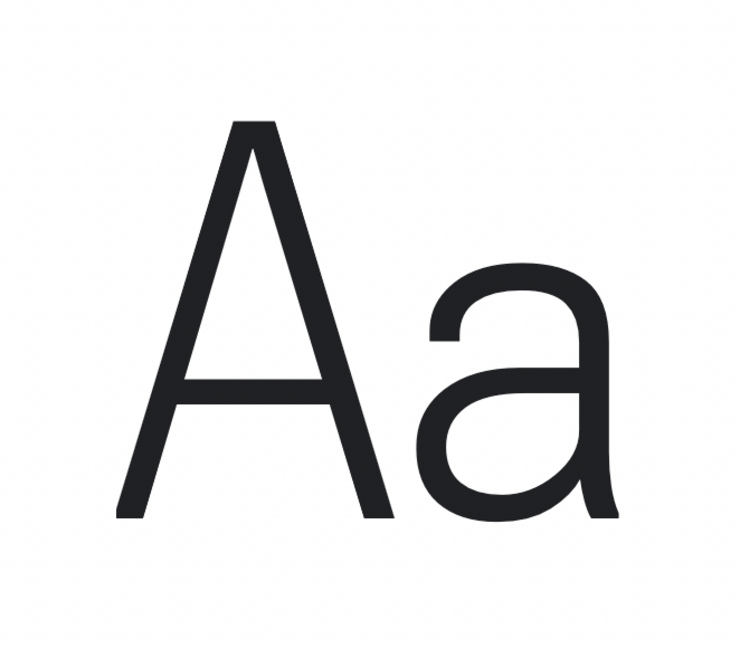
Archivo is a grotesque sans serif typeface family originally designed for highlights and headlines. This family is reminiscent of late nineteenth century American typefaces.
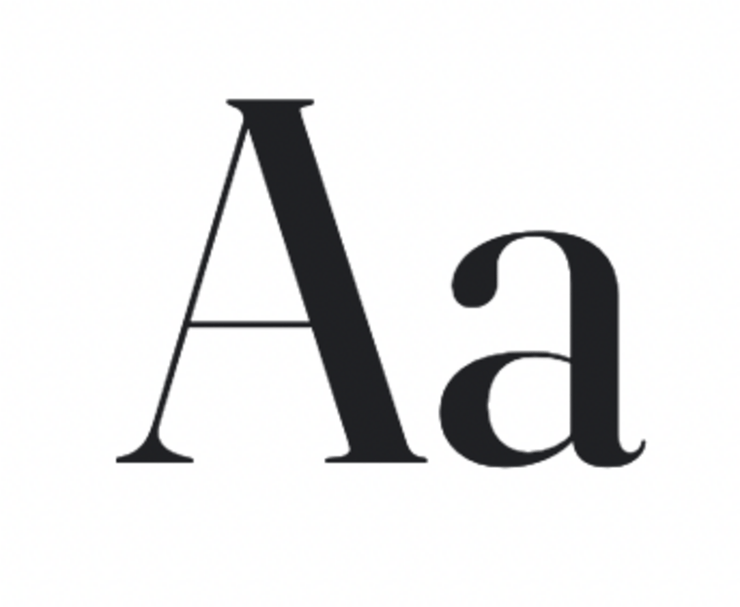
Fraunces is a display, "Old Style" soft-serif typeface inspired by the mannerisms of early 20th century typefaces such as Windsor, Souvenir, and the Cooper Series.
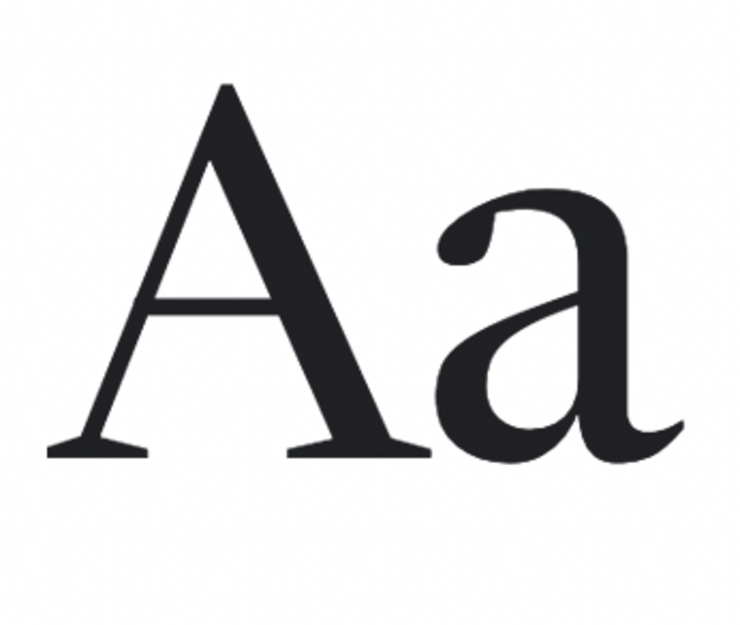
NewsReader is an original typeface designed by Production Type, primarily intended for continuous on-screen reading in content-rich environments.
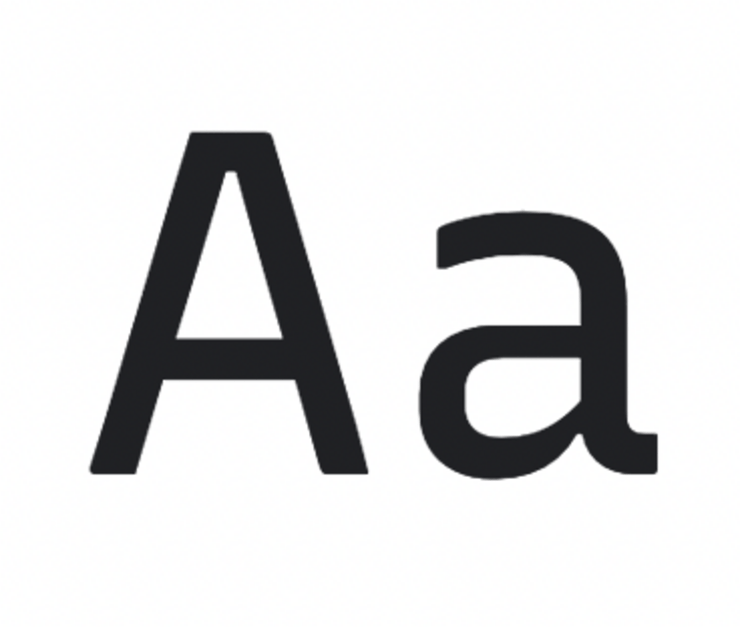
Recursive is typographic palette for UI & code. It draws inspiration from single-stroke casual, a style of brush writing used in signpainting that is stylistically flexible and warmly energetic.
Roboto Flex upgrades Roboto so it becomes a more powerful typeface system. With Flex, you can customize Roboto to express and finesse your text in ways never before possible.
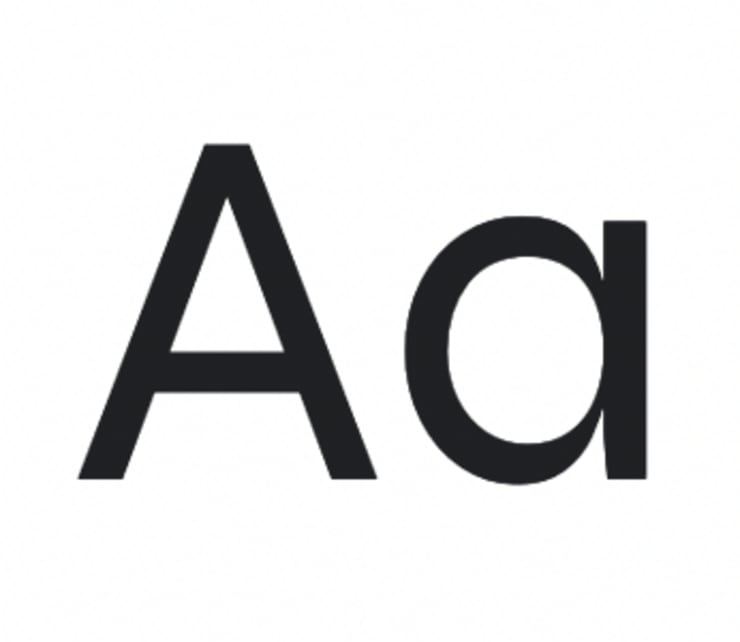
The Syne family was originally designed in 2017 for the Art Center "Synesthésie", based in Saint-Denis — a suburb of Paris. The Art Center aims to gather diverse artistic personalities in order to create new and enriching situations.
En wie de smaak te pakken heeft en zelf een variable font wil ontwerpen: de online video course die Thomas Dahm, Arthur Reinders Folmer en ik ontwikkelden, neemt je bij de hand! De cursus wordt doorlopend gevolgd door ontwerpers van over de hele wereld. 🎈🎈🎈
Why over-collaboration can kill designer creativity and how to avoid that — uxplanet.org
Dat brainstorms alleen werken als ze individueel worden voorbereid, is bekend. Maar co-creatie is op meer plekken een gevaar voor creativiteit. Nick Babich geeft ontwerpbureau's tips – en ik ga ze opvolgen.
This Dinamo tool lets designers and novices customise, rename and download its fonts for free — www.itsnicethat.com
Dinamo is de eerste type foundry die het mogelijk maakt om hun lettertypes aan te passen met alternatieve glyphs. Je kunt zelfs de naam van het font wijzigen; bijvoorbeeld de naam van het bedrijf toevoegen waarvoor je het lettertype koopt. Goed bezig die Zwitsers 👌
Body Margin 8px - The origin story for a style no one wants — www.miriamsuzanne.com
Waarom heeft de body-tag in HTML eigenlijk een default margin van 8px????
Menslies heet de collab van ontwerper Haojun Pan en illustrator Yenk. Hun werk is organisch en analoog, maar ook rete strak en grafisch. Boy oh boy wat mooi.
Eureka, dit is dus de formule! Een element bínnen een ander element geef je minder sterk afgeronde hoeken, maar nu weet ik hoeveel :)
MUST: ANNABEL KEIJZER
Annabel is Halfvetter, illustrator en designer.
Netflix-serie die ik m'n vrienden altijd tip:
The Andy Warhol Diaries. Je hoeft geen Warhol fan te zijn om deze serie tof te vinden. De sfeer, beelden en muziek: het is een fantastisch gemonteerde tijdscapsule.
Of de animatiefilms van Marc James Roels and Emma de Swaef. Via Mubi: This Magnificent cake. Voor wie zich een Vimeo kwartiertje gunt: de korte animatiefilm Oh Willy.
Guilty pleasure Insta account:
Van Instagram raak ik snel verzadigd, maar ik ben verslaafd aan veilingsites. Dé plek om dingen te vinden uit andere tijden. Lampen, stoelen, tekeningen, zeefdrukken, litho’s, beeldende kunst. Ik blijf lang hangen in complete inboedels of partijen schroeven die ik niet nodig heb. Er is zoveel van wat al gemaakt is opnieuw te ontdekken. Neem het werk van Rupprecht Geiger. Nooit van gehoord? Er is zelfs een museum. Als ik daar een recent Instagram-account aan koppel, kom ik op het fantastische werk van Sho Shibuya.
Beste ontwerpadvies dat ik ooit kreeg:
“Wat je maakt, krijg je terug.” Wil je middelmatigheid overstijgen dan zul je eerst iets moeten maken waar je meer opdrachten van wilt hebben. Ik werd mijn eigen opdrachtgever door een typografisch prentenboek te maken. Daar ben ik nooit meer onder gaan werken. Het is niet zo dat ik nu alleen nog maar boeken maak, maar in mijn werk in opdracht komt wel alles samen. Illustreren, schrijven, ontwerpen en sounddesign in één. Digitaal én print.
Ingradients zijn hand-picked mesh gradients.
Polycam is een app die met LiDAR 3D scans maakt.